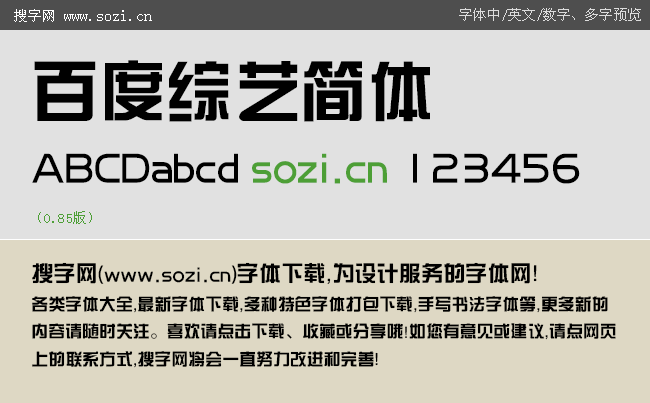
百度綜藝簡(jiǎn)體
搜字網(wǎng)提供一款百度綜藝簡(jiǎn)體下載。綜藝體是黑體的一種變體,也是藝術(shù)字的一種。特點(diǎn)是筆劃更粗,盡量將空間充滿。同時(shí)為了美觀,對(duì)拐彎處的處理較為圓潤(rùn)。適用于廣告、報(bào)刊等的標(biāo)題及海報(bào)展板等設(shè)計(jì)場(chǎng)合使用。
- 風(fēng)格類別: 綜藝體